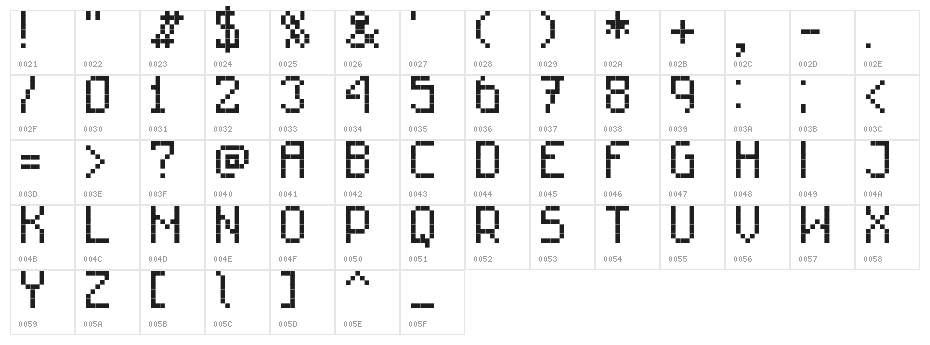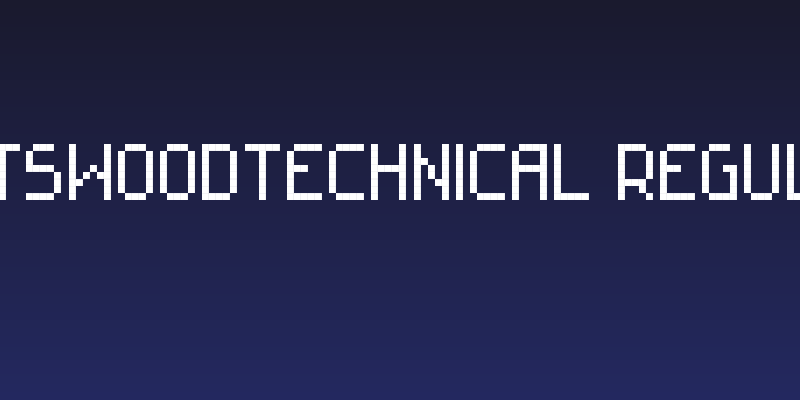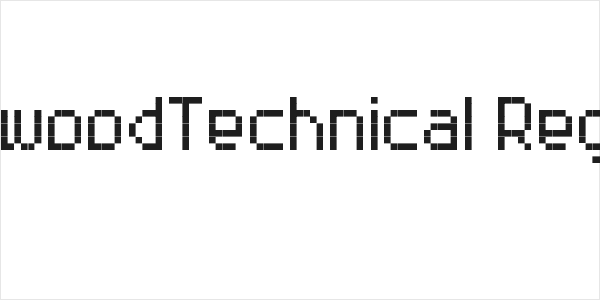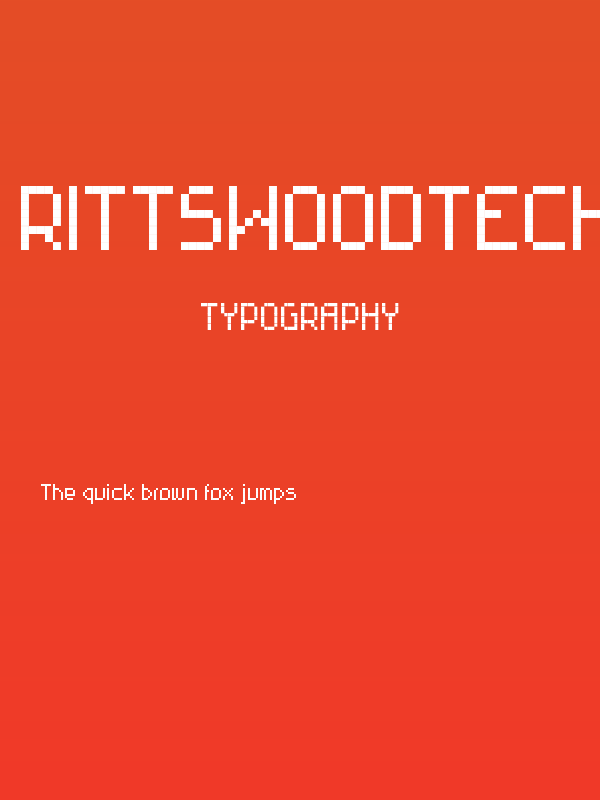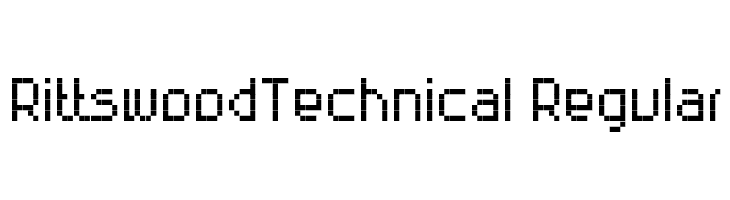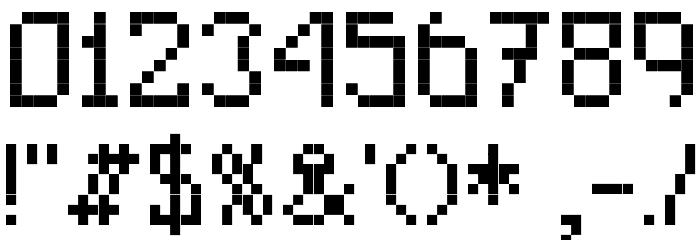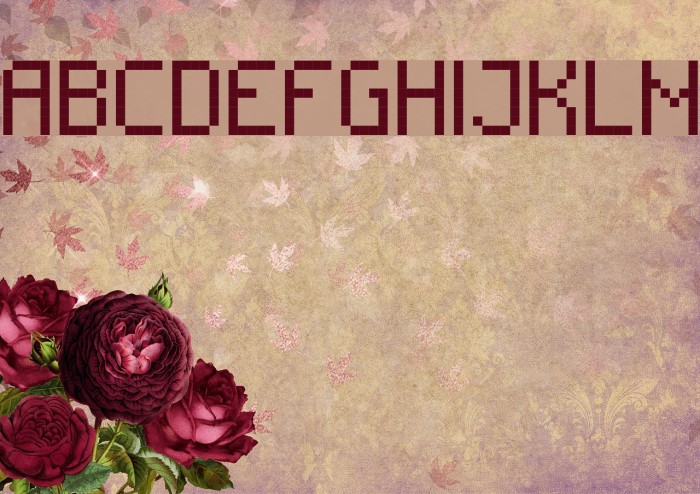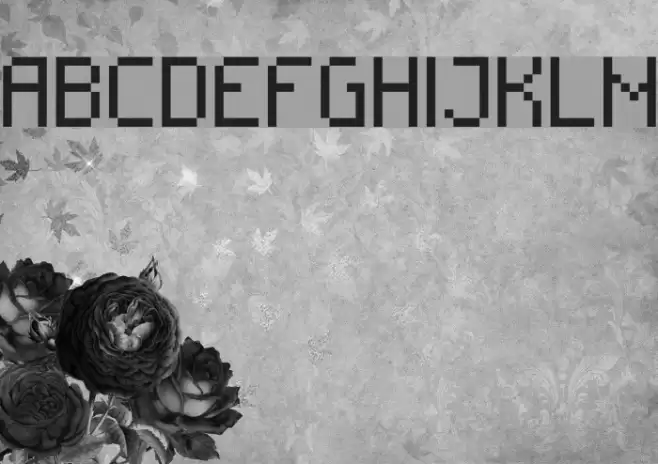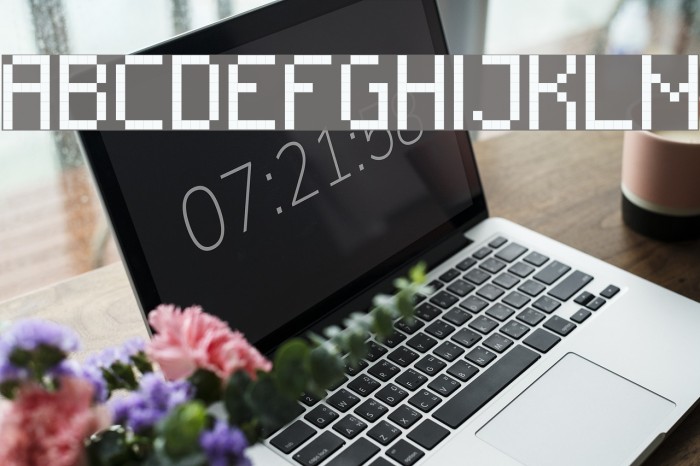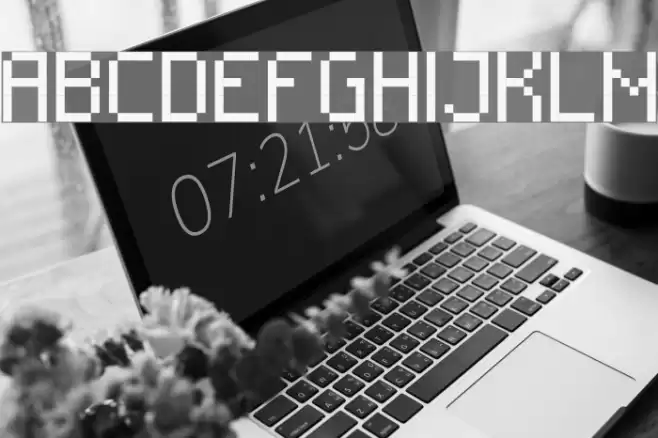
RittswoodTechnical Regular Font
| Categorii | Pixel |
| Stil general | Retro, Digital |
| Caz de utilizare | Logos, Headlines, Digital Art |
| Proiecte propuse | Ideal for retro video game graphics, tech-themed posters, digital art, and any project seeking a nostalgic digital aesthetic. |